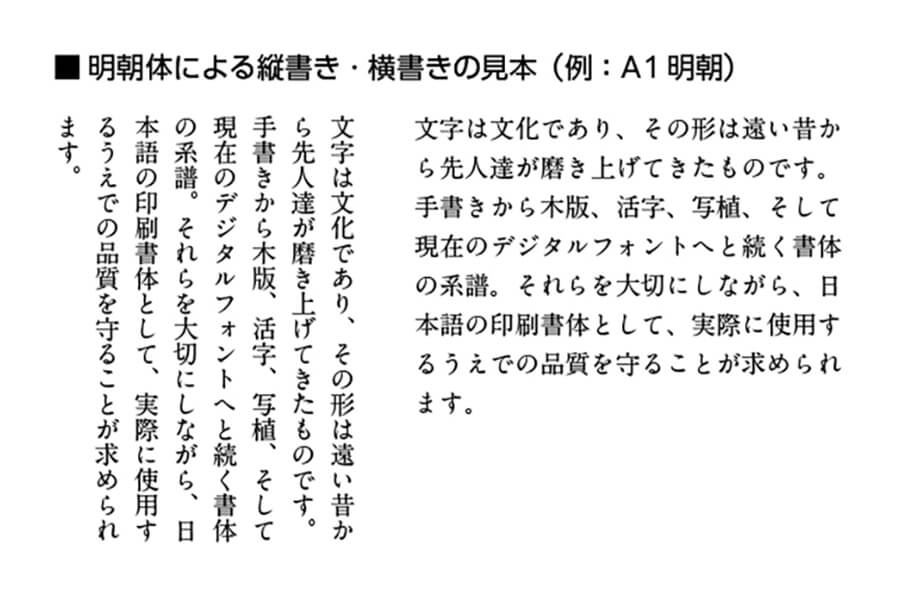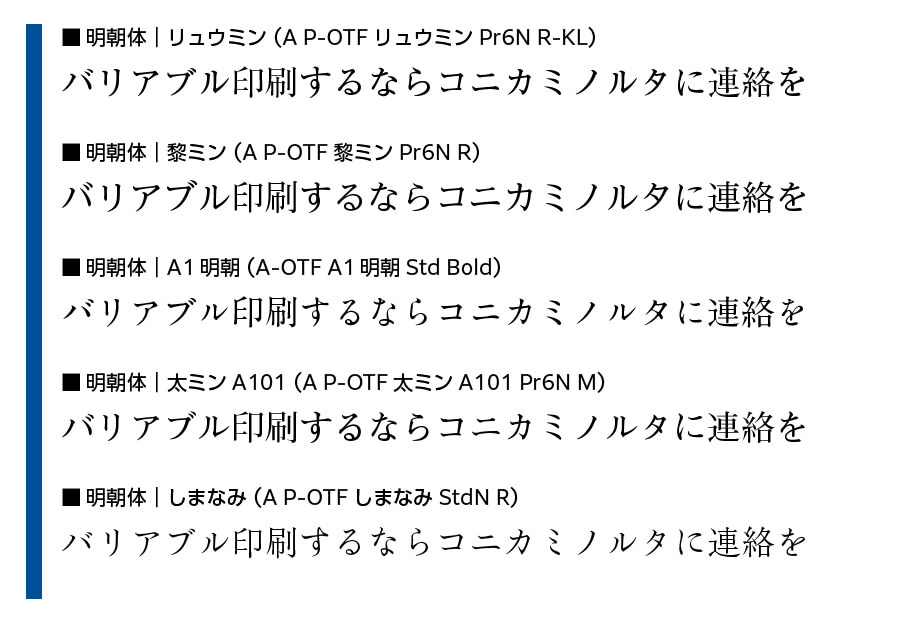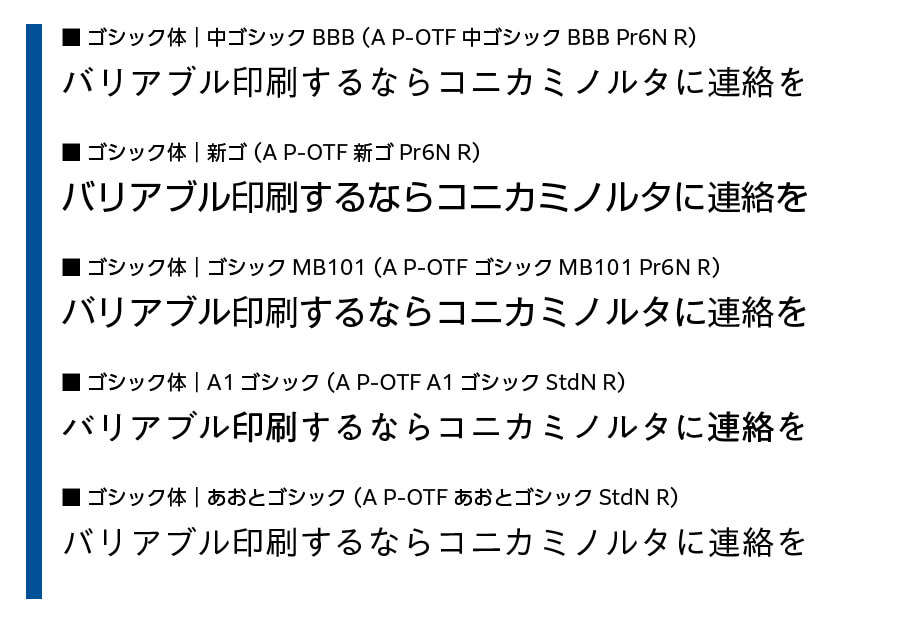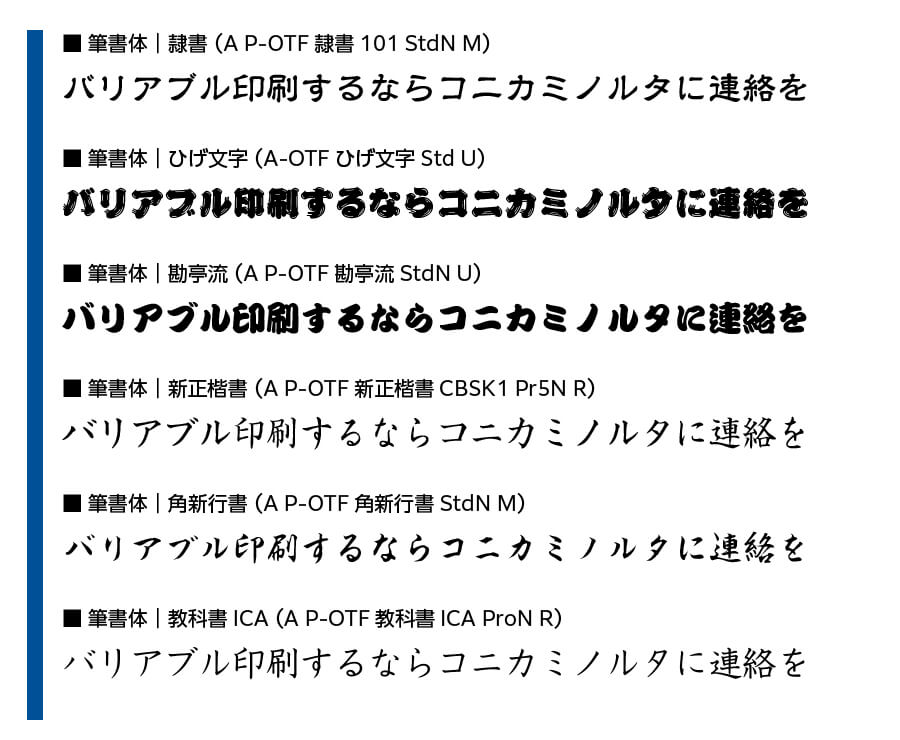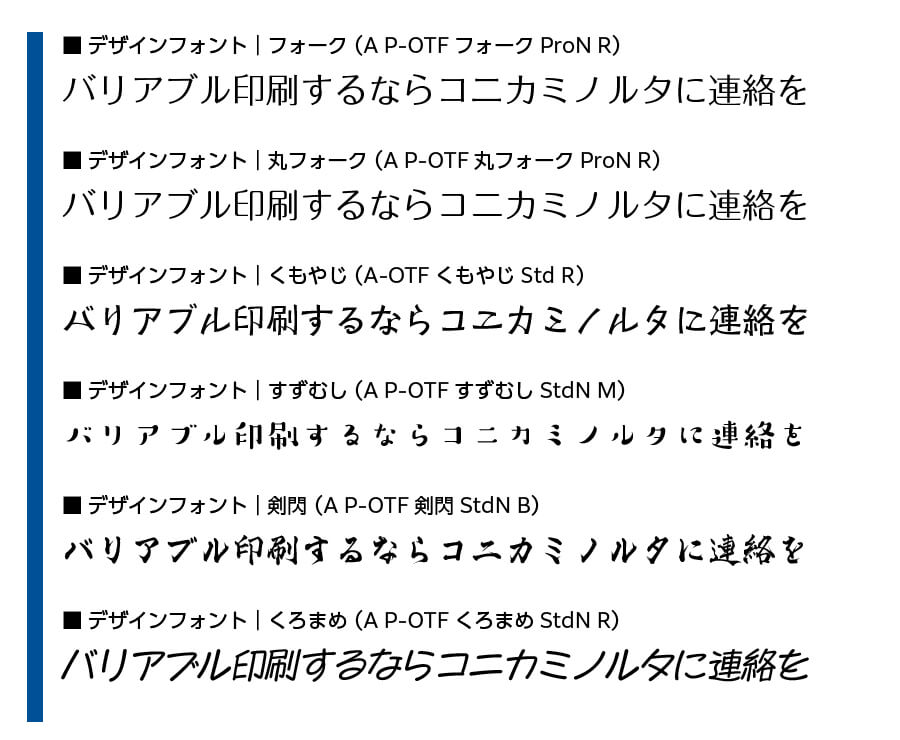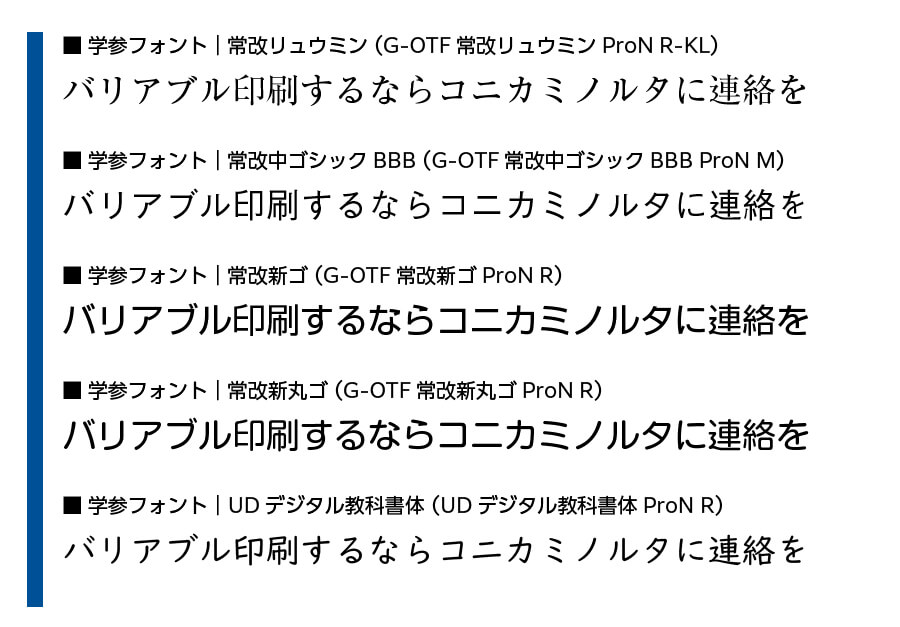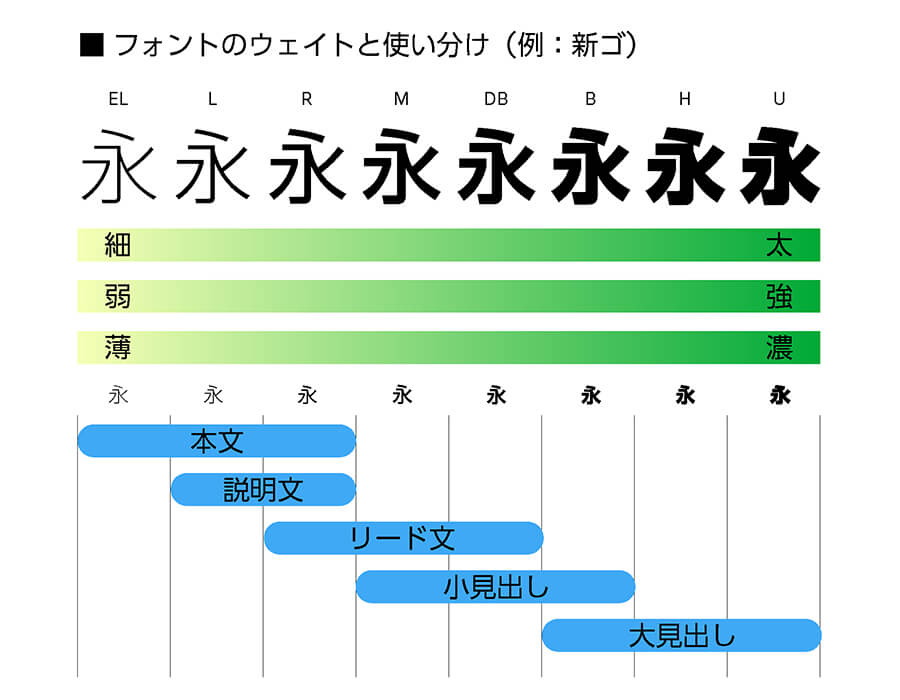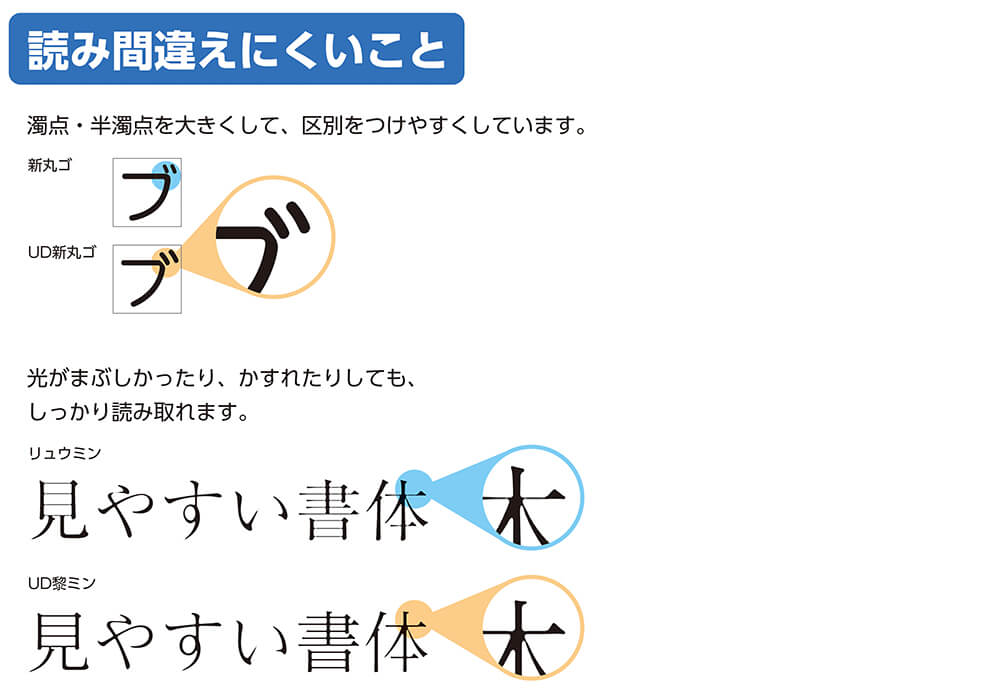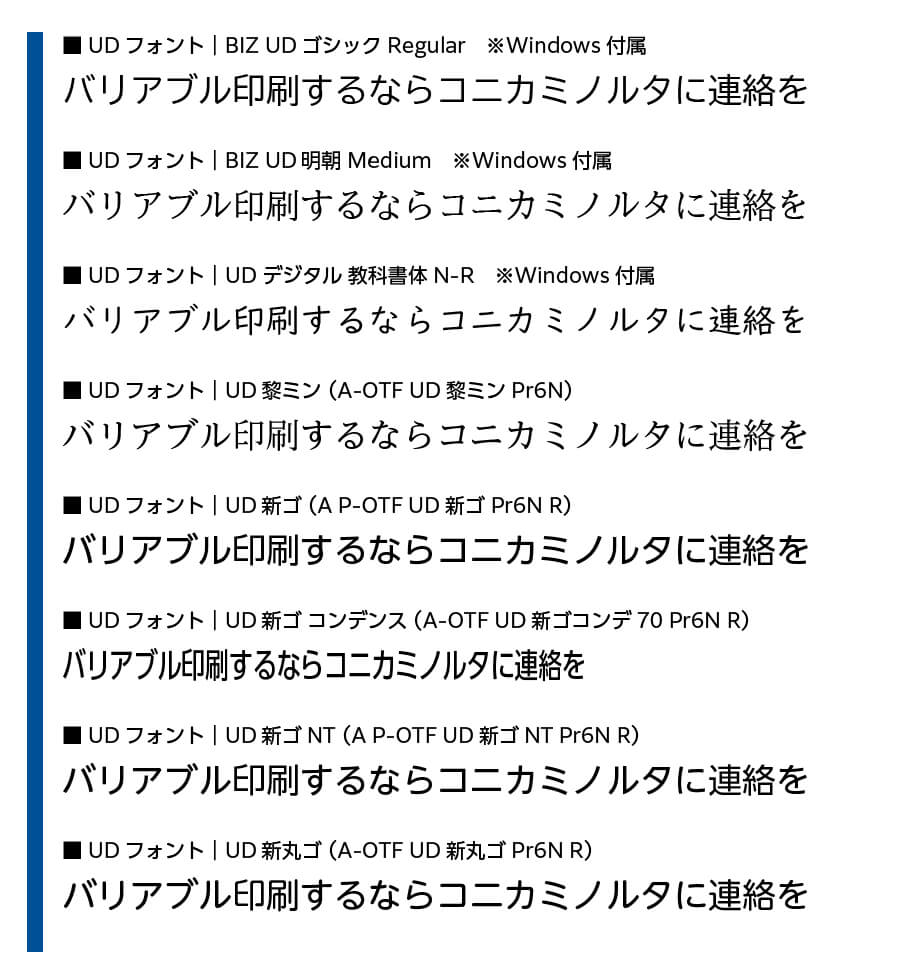
【プロが解説】フォントの種類と使い分け方とは。
読みやすさを追求するために気を付けたいこと
皆さんは、文書やデザインを作成する際に、目的に合わせて使うフォントを選んでいますか?
利用するシーンなどにあわせてフォントを使い分けることは、さまざまな制作物を作るときの重要な要素のひとつになっています。また、内容にマッチしたフォントは相手に情報やイメージを素早く伝えられるため、適切なフォントを使うことは、スムーズなコミュニケーションにも繋がります。
本コラムでは、モリサワのフォントを元に、フォントの選び方やその考え方について解説していきます。
フォントの種類にはどんなものがあるか
日常生活で文字を観察していると、多くのフォントが利用されていることがわかります。
モリサワだけでも現在では2,000種類を超えるフォントをご提供しています。もちろん、他のフォントメーカーさんからも多数のフォントが提供されていますから、世の中にあるフォントの数だけでもおそらくは何万種類にもなるでしょう。
ここでは日本語フォントの主だった種類・分類について、モリサワフォントの代表的なフォントを見本に挙げながら、ひとつずつ解説していきます。
明朝体
一般的に利用される書体のひとつです。特徴としては、一般的には縦線が横線に対して太いこと、線に強弱があり、とめ、はね、はらいなどの、筆で描くような抑揚が文字の要素にありながらも、手で書くのとは異なる骨格である点が特徴となっています。
見たときにフォーマルな印象を与えることから、ビジネス文書の作成でも、明朝体はよく利用される書体のひとつになっています。
一般的に、多くの明朝体は文字の中心を基準とした揃いと読むときの繋がり、目線としての追いやすさなどから、縦書きとの相性が良いため、小説や新書などの文章では明朝体が多く利用されています。
個々の書体にもよるのですが、横書きで利用すると文字の間が空き気味に見えることがあるため、その点を考える必要があります。
モリサワの代表的な明朝体は「リュウミン」で、古くから多くの印刷物に利用されてきました。その他の明朝体としては、横線のバランスを取りながらさまざまなシーンで利用できるようにバリエーションを広げた「黎ミン」や、交差する部分に墨だまりというにじみ的な要素を持つ「A1明朝」が、デザイン的な要素も加味して利用されることが多くなっています。
その他にも、モリサワフォントの利用者に長く愛されている「太ミン A101」や、毛筆のニュアンスを取り入れた新しいフォント「しまなみ」もラインナップとして揃っています。
ゴシック体
名称としては、角ゴシックと呼ばれることもあります。明朝体とは異なり、縦線・横線ともに同じ太さに見えるようデザインされ、線の強弱も基本的にはあまりない、画一的な形状に見えるのが特徴です。明朝体よりも歴史が浅いこともあり、比較的モダンな印象を与えるといわれています。明朝体よりも視認性が良いことと同時に、横組みした場合にも読みやすいことが多いといわれます。
モリサワが提供する代表的なゴシック体は「中ゴシックBBB」で、モリサワの歴史としても長く提供していることや、細目のバランスのために長い文章にも利用しやすい点が挙げられます。公共的な場所でよく利用されるものとしては「新ゴ」があり、字面が大きく見える状態でデザインされていることや、中ゴシックBBBと比べると、よりモダンな雰囲気を与えることから、幅広く利用されています。新ゴよりは多少小ぶりではあるものの、力強さを感じさせる「ゴシックMB101」も利用されることが多いゴシック体です。
モリサワが提供する中で比較的新しいものとしては、A1明朝の骨格や墨だまりを受け継いだ「A1ゴシック」、デジタル時代のディスプレイ表示でも読みやすさを追求した「あおとゴシック」があります。
丸ゴシック体
先端の形状が角張っているゴシック体に対して、丸く処理されているのが丸ゴシック体です。ゴツゴツする印象を与えるゴシック体に対して、やわらかな印象を与え、親しみやすく感じるのが丸ゴシック体といえます。こちらも公共的な場所での利用が比較的多いこと、そして細めの丸ゴシック体は読みやすさを考慮して長文などに利用されることがあります。
モリサワで代表的な丸ゴシック体は、古くから提供している「じゅん」が挙げられます。じゅんよりモダンな特徴を持つのが、字面が大きくデザインされている「新丸ゴ」です。他にも、新ゴの骨格を元にしながら丸ゴシックの特徴を持たせた「ソフトゴシック」もあります。
筆書体
人の手で書いたような特徴を多く残したフォントが筆書体(ひっしょたい)です。筆や硬筆などで描く、はね、とめ、はらいを含む、文字の形について手書きの風合いを考慮してデザインしていることが特徴です。
それだけ聞くと明朝体と同じように思えたりするのですが、明朝体やゴシック体は、たとえば之繞(しんにょう)の縦棒がまっすぐになるのに対し、筆書体の場合は原則として手書きのように曲がっているなど、運筆としての風合いを残す点が異なっていたりします。しかし、筆書体というだけではかなり大雑把な括りになり、具体的にはさまざまな種類があるのが実際です。
日本語フォントの筆書体の中には古い中国の文字を基準にデザインされたものもあり、代表的なものとしても、篆書(てんしょ)、隷書(れいしょ)、行書、草書(そうしょ)、楷書(かいしょ)などがあります。また、日本の江戸時代に生まれて発展した、勘亭流や寄席文字、髭文字もあります。そして、明治初期に作られたといわれ、その名の通りの利用を主体とした教科書体も、筆書体の範疇に入ってきます。
モリサワでもこの筆書体の種類を豊富に用意しており、伝統的な内容を含むデザイン作成だけではなく、逆に現代的な内容であっても利用するようなケースも世の中では少なからず見受けられます。
デザインフォント
今までご紹介した分類のように、長く利用されてきたり元の出自が古い文字とは異なるものの多くが、デザインフォントとしての分類になります。
文字を作ることは、昔は設備として考えられていたことや、金属活字として作ることもあって、基本的な文字を中心に利用することが一般的なものとなっていました。以前は金属活字をとり揃えたり、ガラスの文字盤を専用の機械で写真撮影するなどで文字を印字していたため、専門の業者や印刷会社でしか取り扱うことはできなかった、という点もありますので、整った文字を使うこと自体が今ほど容易ではなかったのです。
ちなみにモリサワは、もともと写真の技術を応用して文字を印字する機械「写真植字機」を開発・販売していたメーカーでした。
しかし、文化や歴史の発展によりデザインを生業(なりわい)とする方が増えたこと、デザインをするための手段である道具が進化したことなどを背景に、現在ではさまざまな形状のフォントが毎日のように発表されています。
特に現代ではコンピューターを使ってデザインをすることが常態化したこともあり、プロのデザイナーだけではなく、一般の方でもフォントを作れるようになってきています。
モリサワのデザインフォントも多彩なラインアップが用意されています。シンプルながら使いやすい「フォーク」「丸フォーク」、文字のパーツを繋いだような「くもやじ」、抑揚がありアンバランスのように見えながらかわいらしい印象を持つ「すずむし」、筆書系を思わせつつも力強さのある「剣閃」、ペンで勢いよく手書きしたような印象の「くろまめ」などがあります。
学参フォント
筆書体の中のひとつで教科書体がありましたが、現在では教科書体以外にも多くのフォントが学校の教科書や学習用フォントとして用意されています。その分類がこの「学参フォント」です。学参フォントの役割としては「文字を習いはじめた人が手書きで書くときに混乱しないこと」であり、文部科学省の学習指導要領に準拠するようデザインされている点が特徴となっています。
モリサワの場合、明朝体であるリュウミン、ゴシック体である中ゴシックBBB、丸ゴシックの新丸ゴなどを、学参基準のフォントとして利用できるようにデザインを見直したものを用意しており、それらのフォントがこの分類として挙げられます。
また最近でいえば、後ほどご紹介する「UDフォント」の区分にも含まれる「UDデジタル教科書体」もこの学参フォントになります。もちろん、モリサワで以前から用意している教科書体「教科書ICA」も、学参フォントの種類に含まれます。
モリサワでは、他にもさまざまなフォントをラインナップしています。モリサワのサイトでは「書体見本」のページを設けており、書体の分類や種類、利用言語などから絞り込んだり、任意の文字を入力してどのような状態になるのかを確認することができますので(※)、ぜひアクセスして実際に確認してみてください。
※ 一部のフォントは試すことができません
ただ、いままでの内容で見てわかるように、フォントの分類は、現在ではひとつの括りに収まらないことがあります。デザインフォントでも明朝風、ゴシック風、筆書体風のものも数多くあり、分類の区分が曖昧になる場合があるためです。フォントメーカーの人間がこう言ってはいけないのかもしれませんが、フォントの分類については、ひとつの目安としておくのがいいかもしれません。
フォントを選ぶための基準とコツ
皆さんは文書やプレゼン資料を作成するとき、どのようなフォントを使っていいのか悩むことはありませんか? どんなフォントが合っているのか、本当にこのフォントは読みやすいのか、その結果として渡す先の人に評価してもらえるか、なんてことを考えることもあるかもしれません。
前の項ではフォントの分類についてご紹介しましたが、実はその把握を行うことは、フォントを適切に、そして素早く選ぶためにも必要なことになっています。特に普段からよく利用するフォントについては、分類を覚えておくだけでもすばやく選ぶことができるようになります。そのうえで分類ごとの特徴も押さえておくと、フォントの使い分けがしやすくなるでしょう。
明朝体
さまざまなシーンで利用ができる分類の一つです。基本的には癖が少なく、多くの文書にマッチングしやすいため、見出しや長文などあらゆる利用に適している、オールラウンダーなフォントといえます。特にフォーマルな文書など、利用シーンによっては明朝体のみの利用が求められることもあります。見出しを含む文書については、読みやすさを考慮してゴシック体と組み合わせて使うことも考えてみましょう。また、すでに出している画像にあるように、利用する明朝体の特徴によっては、横組みで使うと隣り合う文字とのスキマがあるように見えるので、選んだフォントが縦組み向きなのか横組みにも使って問題はないのかを考慮するほうがいいでしょう。
ゴシック体
明朝体と同様、さまざまなシーンで利用しやすい分類です。縦線・横線の太さが均一である特徴から、明朝体よりも視認性が高くなるケースがあるため、同じような太さのフォントを使う場合、少し小さい文字でも読みやすさに長ける特徴があります。プレゼン資料についてはプロジェクターによる表示のことを考えると、基本的にはゴシック体を基準にして利用するのが望ましいでしょう。
丸ゴシック体
ゴシック体に類する点があるので、プレゼン資料への利用はしやすいと思います。また看板などの表示などにも利用しやすいといえるため、社内に掲示するような案内に利用することも適しています。ただ、丸っこい形状を考えると、フォーマルな文書への利用はミスマッチといえるでしょう。
通常の文書やプレゼン資料作成の中で文字周りの対応に注意しつつも、UDフォントの利用も行うことで、より効果的な「読みやすさ」について対応していただくことについて、この記事をきっかけに、皆さんもぜひ考えてみてください。